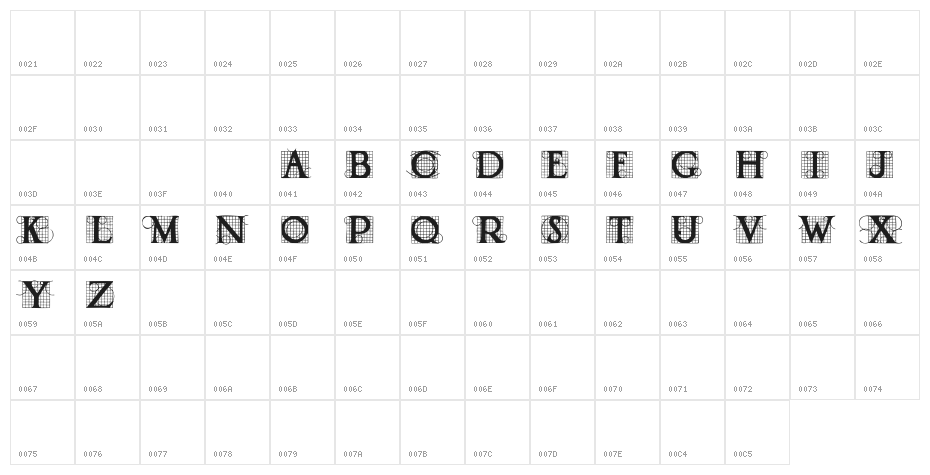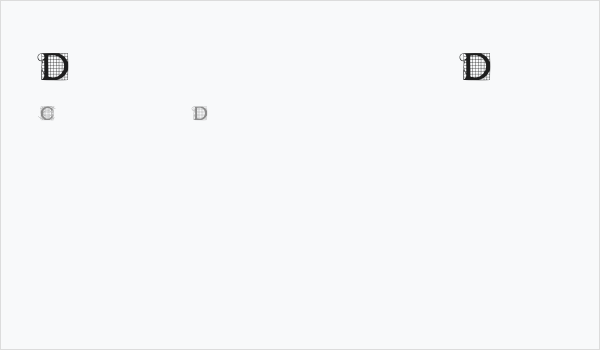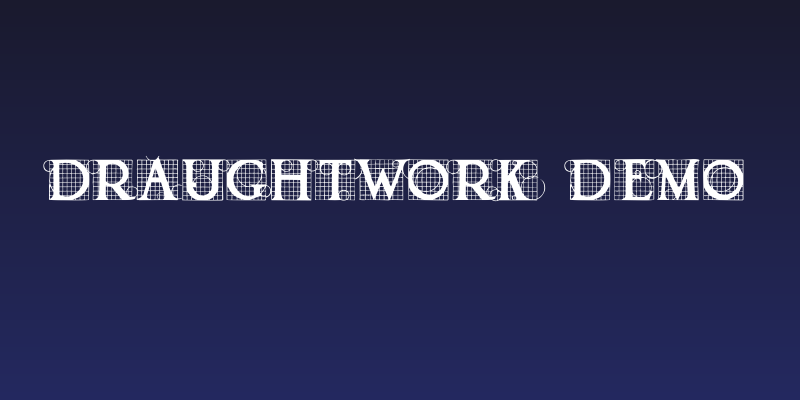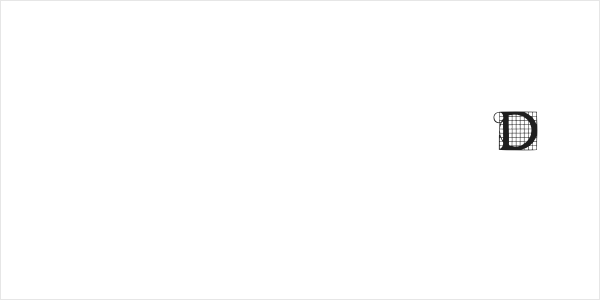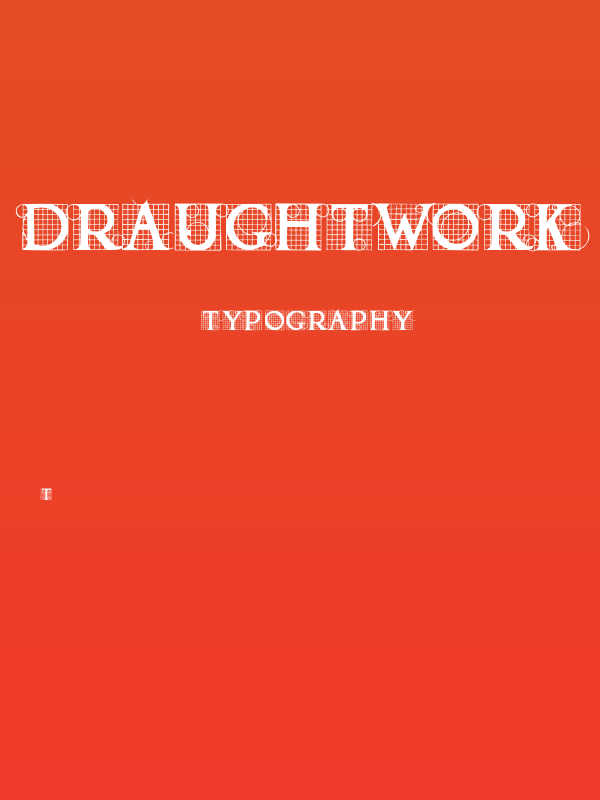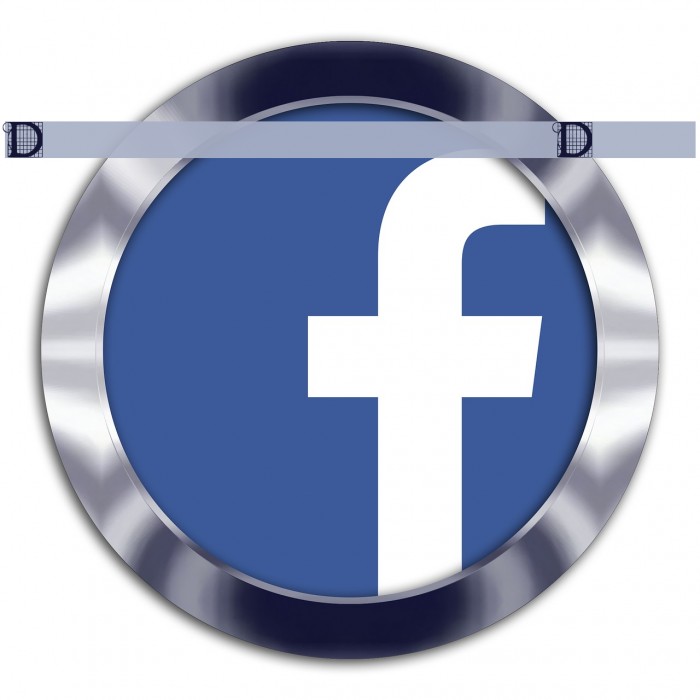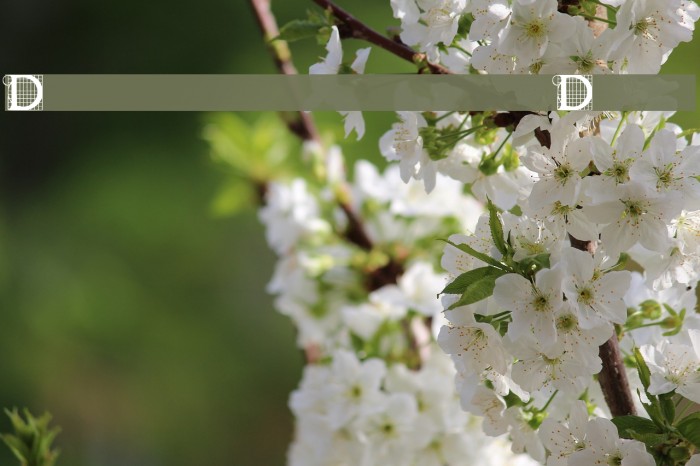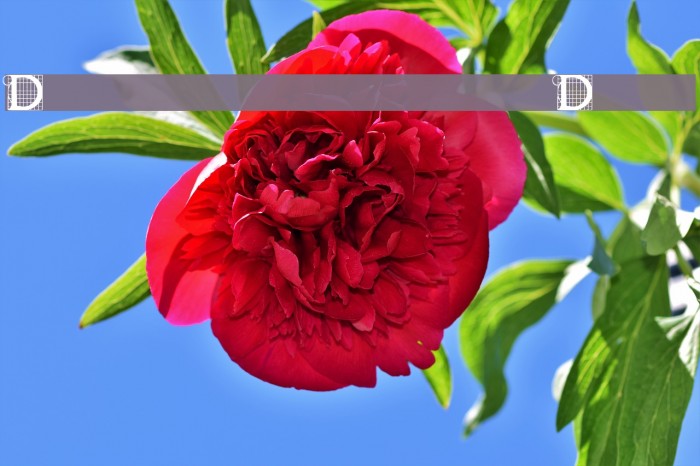
Draughtwork Demo Font
Fonts by The Scriptorium - Dave Nalle
| Gesamtstil | Technical, Industrial |
| Vorgeschlagene Projekte | Ideal for architectural magazines, technical manuals, industrial-themed posters, and branding for engineering firms. |